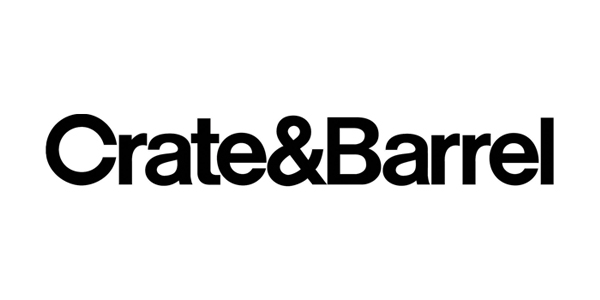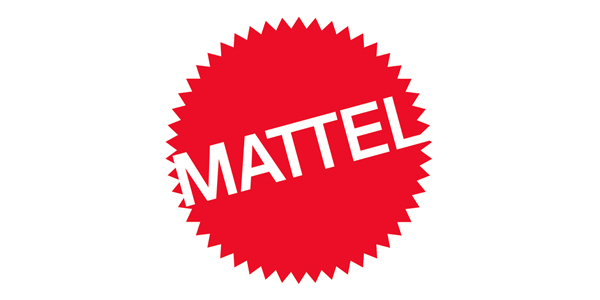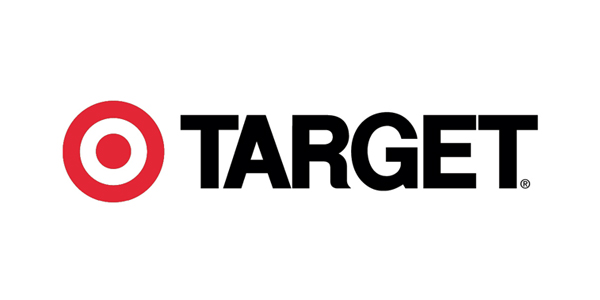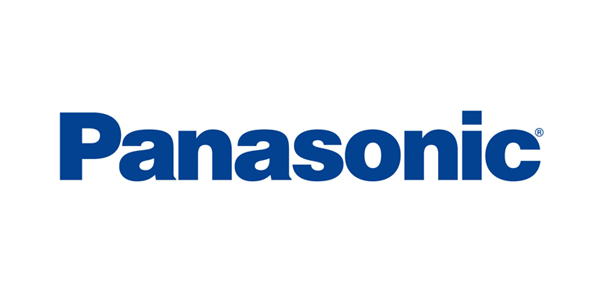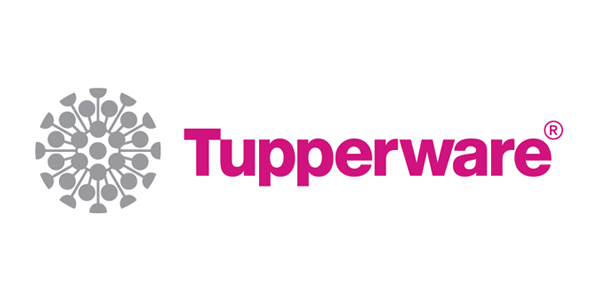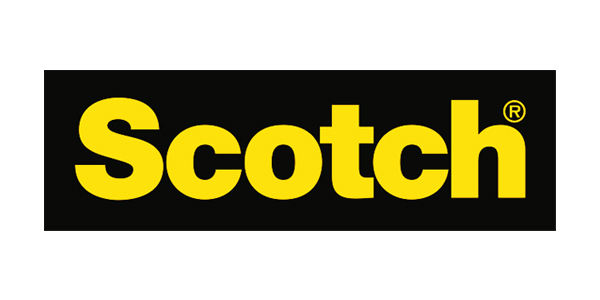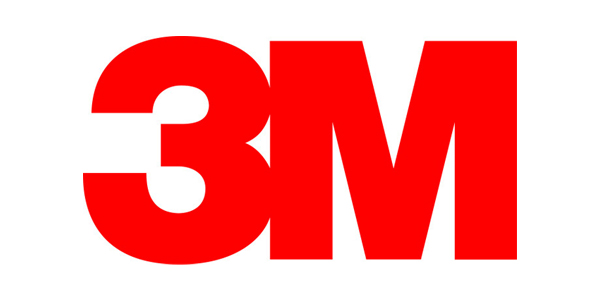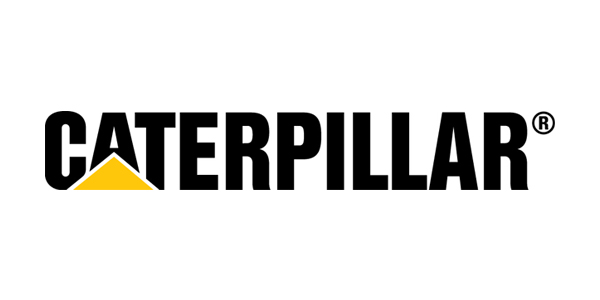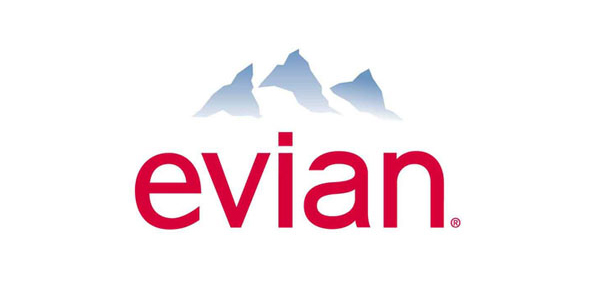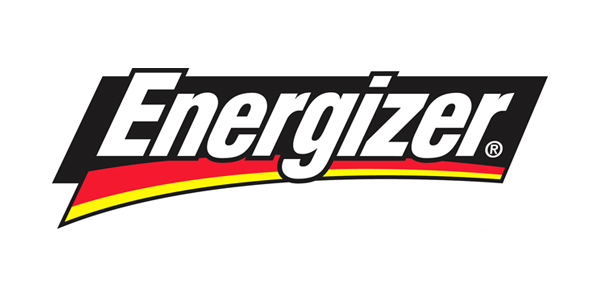
La tipografía Helvetica es una de las fuentes más reconocidas (y reconocibles) del mundo. Su relevancia en el mundo del diseño gráfico se ha mantenido imbatible a lo largo de los años, siendo a día de hoy una de las familias tipográficas más utilizadas en la creación de todo tipo de proyectos gráficos. Helvetica es un tipo de letra distinto, elegante y profesional, con multitud de variantes diferentes y perdurable en el tiempo, siendo la tipografía elegida por multitud de grandes firmas para representar el nombre de su marca. A continuación, os mostramos algunos ejemplos de conocidos y excelentes logotipos creados con la fuente Helvetica.
1. Jeep
2. Crate&Barrel
3. American Airlines
4. Staples
5. American Apparel
6. Lufthansa
7. Nestlé
8. Toyota
9. Post-it
10. BMW
11. Mattel
12. Target
13. Panasonic
14. Tupperware
15. Scotch
16. 3M
17. Caterpillar
18. Evian
19. Skype
20. Energizer
21. CVS Pharmacy